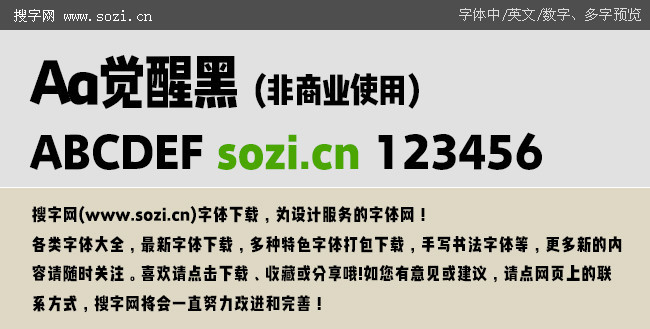
Aa覺醒黑
搜字網(wǎng)給大家提供一款A(yù)a覺醒黑(非商業(yè)使用)中文字體下載,該字體是一款醒目的標(biāo)題字體,字體筆觸適中,字形端正,清新簡(jiǎn)明,具有強(qiáng)烈的視覺沖擊力。適合書裝設(shè)計(jì)、包裝設(shè)計(jì)、海報(bào)設(shè)計(jì)等應(yīng)用(此字體為個(gè)人非商用版,商用可以聯(lián)系QQ:1006760504)。